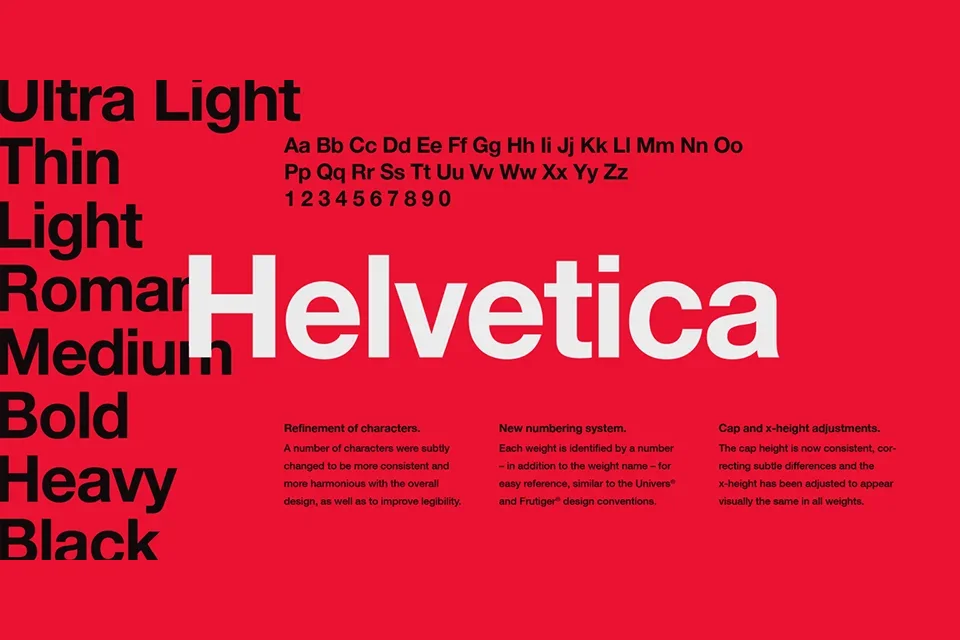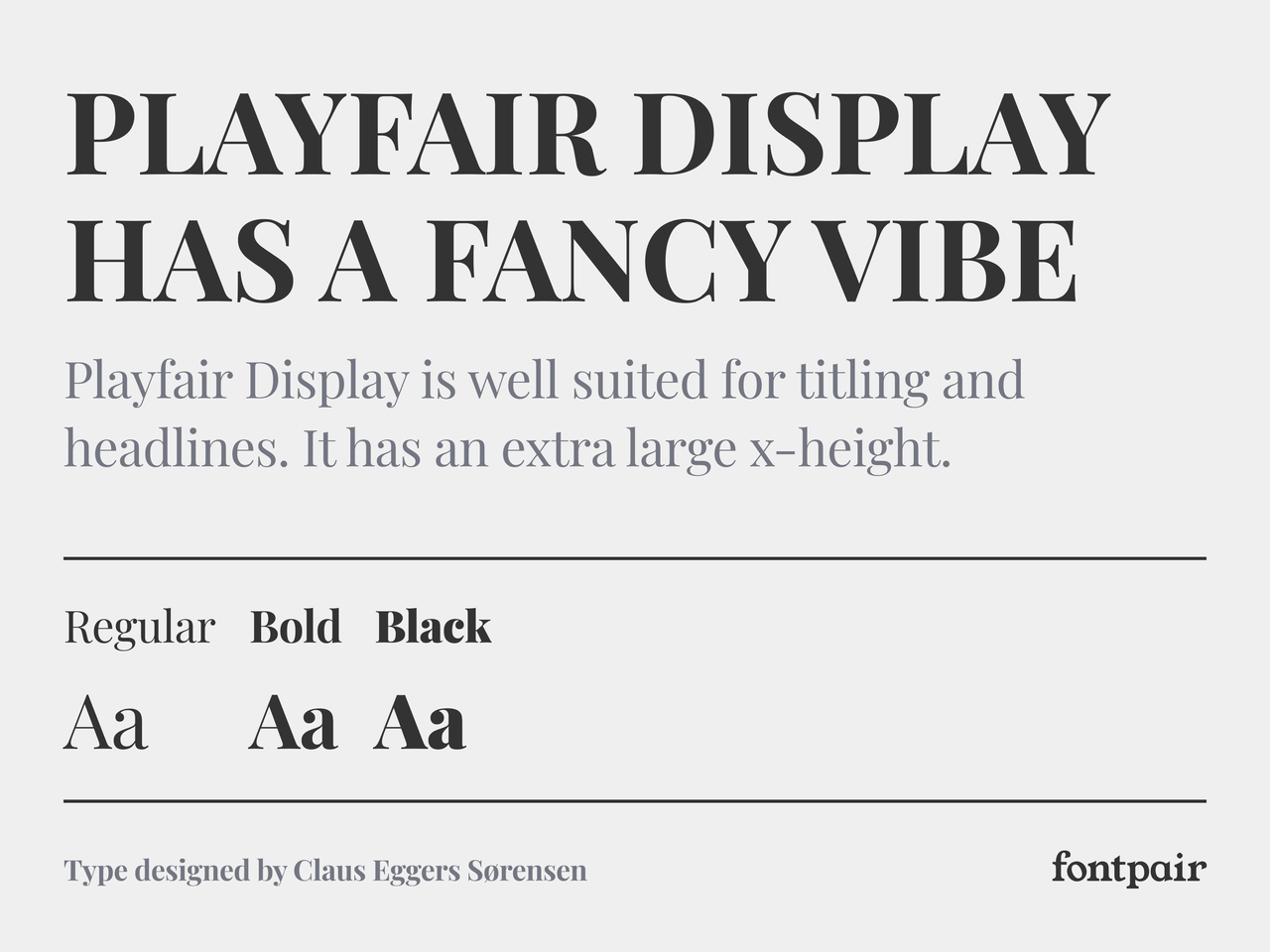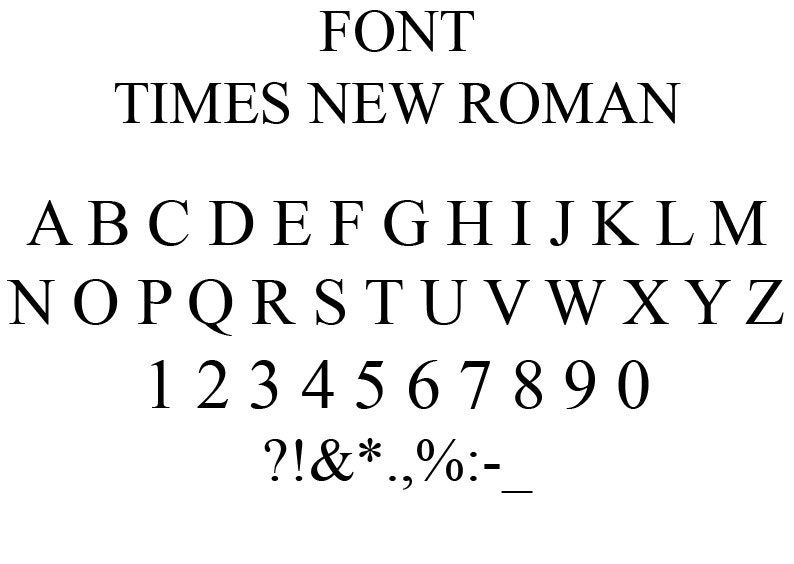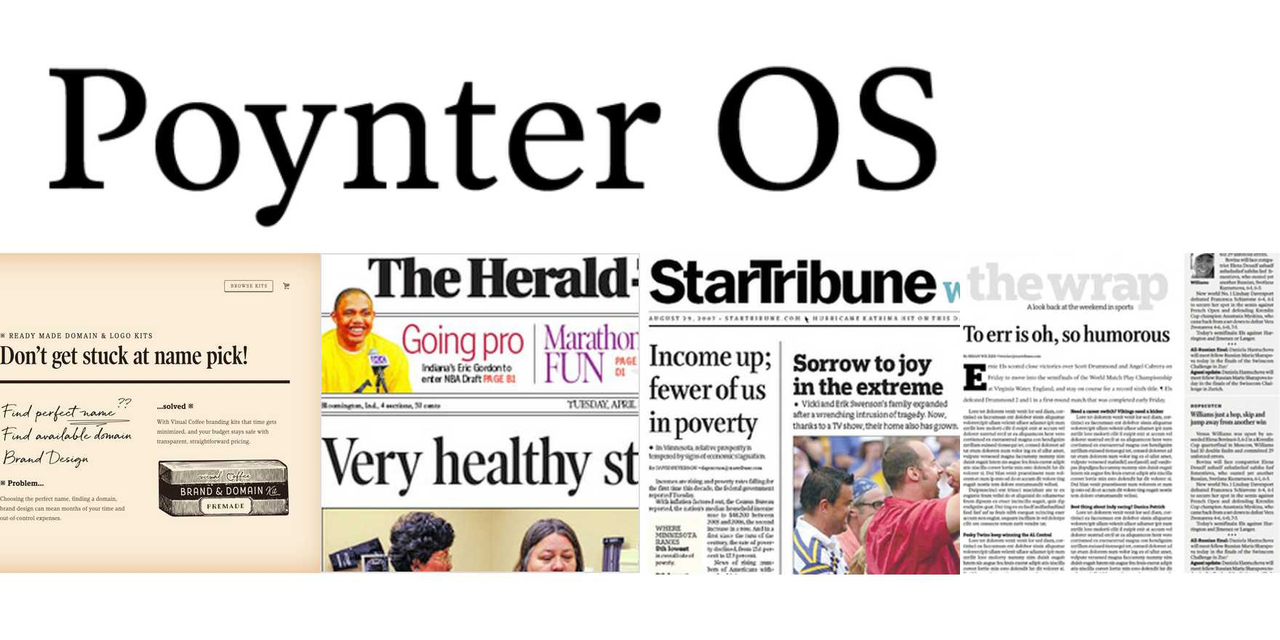
Verwenden Sie Nachrichtenschriften für modernen Journalismus | verbessern Sie die Wahrnehmung der Leser
Entdecken Sie einfach zu bedienende Nachrichtenschriften und bringen Sie Ihre Schlagzeilen zum Strahlen. Entdecken Sie Möglichkeiten, diese Schriftarten effektiv in Artikeln, Blogs und Beiträgen in sozialen Medien zu verwenden. Verwenden Sie außerdem den CapCut Desktop-Video-Editor, um dynamische Nachrichtentext-Effekte zu Videos hinzuzufügen und zu bearbeiten.
Eine kraftvolle Schlagzeile kann der ultimative Blickfang sein, um die Zuschauer sofort in Ihre Geschichte hineinzuziehen. Die richtigen Nachrichtenschriften sind wichtig, um den Ton anzugeben und Dringlichkeit, Glaubwürdigkeit oder Neugierde zu vermitteln. Von kühnen, modernen Schriftarten bis hin zu zeitlosen Serifenoptionen kann Ihre Wahl die Stimmung bestimmen und die Botschaft mit einer deutlichen Note verstärken. In diesem Leitfaden werden wir daher die wichtigsten Nachrichtenschriften und -quellen untersuchen, um Schlagzeilenschriften zu erhalten.
Erstellen Sie einzigartige Blogs mit den besten aktuellen Nachrichten-Schriftarten
Die Verwendung der besten Eilmeldungen-Schriftarten für Ihren Blog sorgt für Schlagzeilen, die Aufmerksamkeit erfordern und Autorität vermitteln. Diese Schriftarten wurden für eine einfache Lesbarkeit und eine mutige Wirkung entwickelt, um Schlüsselbotschaften effektiv hervorzuheben. Ihr einzigartiger Stil kombiniert die Schärfe von traditionellem Zeitungspapier mit einem modernen Touch, um ein unverwechselbares, maßgebliches Erscheinungsbild zu schaffen. Die Integration dieser Schriftarten in Ihren Blog sorgt für mehr Professionalität und macht Ihre Inhalte unvergesslicher.
Die 5 besten Schriftarten für Nachrichten-Websites zum Ausprobieren
Die Wahl der richtigen Schriftart kann einen großen Einfluss darauf haben, wie die Leser Ihre Inhalte wahrnehmen und sich mit ihnen auseinandersetzen. Hier sind fünf erstklassige Schriftarten, die Ihrer Nachrichten-Website Lesbarkeit und Stil verleihen können.
1. Zeiten New Roman
Eine klassische Serifenschrift, Times New Roman, ist seit langem ein Favorit für ihre Professionalität und Lesbarkeit. Ihr traditionelles, raffiniertes Aussehen macht sie perfekt für Nachrichtenseiten, die Autorität und Vertrauenswürdigkeit vermitteln wollen.
The 5 best fonts for news websites to try: Times New Roman
2. Helvetica
Helvetica ist eine sehr lesbare serifenlose Schrift, die für ihre klaren Linien und ihre moderne Ausstrahlung bekannt ist. Sie eignet sich hervorragend für die Erstellung geradliniger, übersichtlicher Überschriften, die den Leser ohne Ablenkung auf den Inhalt konzentrieren.
The 5 best fonts for news websites to try: Helvetica
3. Poynter
Der speziell für Zeitungen entwickelte serifenförmige Stil von Poynter optimiert die Lesbarkeit und spart Platz, wodurch er sich für Artikel mit hoher Wortzahl eignet. Er ist sowohl für Überschriften als auch für Textkörper sehr vielseitig einsetzbar.
The 5 best fonts for news websites to try: Poynter
4. Franklin Gothic
Franklin Gothic bietet einen kühnen, eindrucksvollen Look, der sich gut für Schlagzeilen und wichtige Ankündigungen eignet. Es hat eine einzigartige Persönlichkeit, die Klarheit bewahrt und Nachrichtenlayouts einen modernen Touch verleiht.
The 5 best fonts for news websites to try: Franklin Gothic
5. Playfair-Anzeige
Mit seiner eleganten serifenförmigen Struktur bringt Playfair Display Raffinesse in Nachrichten-Websites. Sein kontrastreiches Design eignet sich gut für Feature-Artikel und Meinungsartikel, um Stil zu verleihen, ohne die Lesbarkeit zu beeinträchtigen.
The 5 best fonts for news websites to try: Playfair Display
1. Was ist der beste Schriftstil für aktuelle Nachrichten?
Kühne, aufmerksamkeitsstarke Schriftarten eignen sich in der Regel am besten für aktuelle Nachrichten, um eine unmittelbare Wirkung zu erzielen. Serifenlose Schriftarten wie Helvetica oder Bold-Serif-Optionen eignen sich gut, um ein Gefühl von Dringlichkeit und Klarheit zu schaffen. Für einen optimierten Prozess bei der Gestaltung Ihrer Schlagzeilen können Sie den CapCut Desktop-Video-Editor verwenden, um verschiedene Schriftstile mit zusätzlichen Funktionen wie Textanimationen und erweiterte Textsynchronisation für dynamische Videopräsentationen zu implementieren.